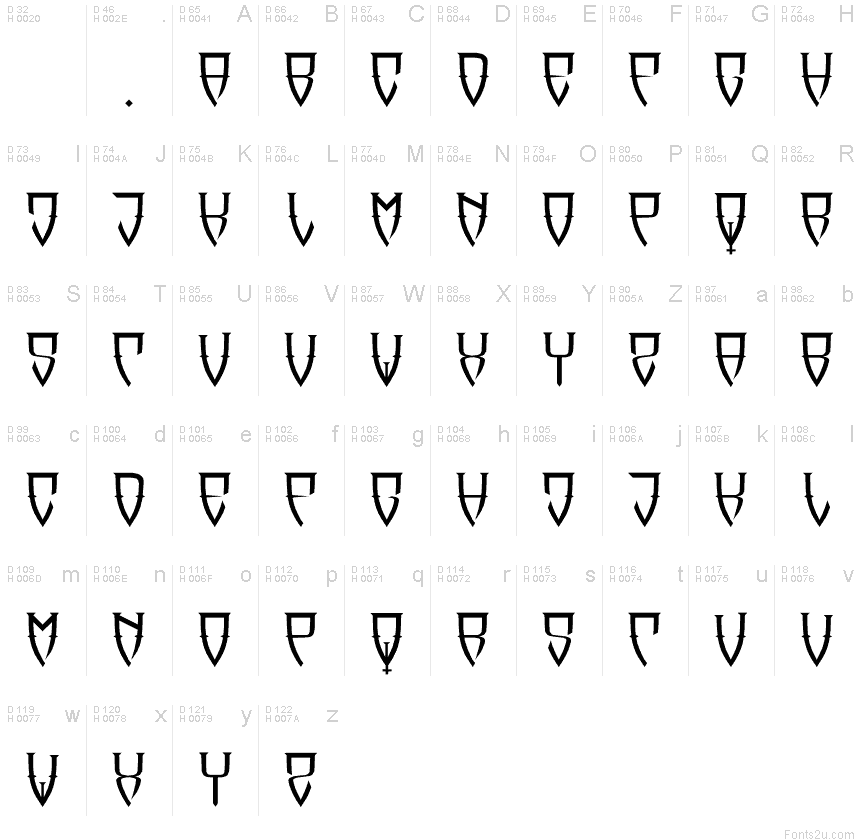
Reubalach di Rzy/SD è un font gotico moderno gratuito composto solo da maiuscole, caratterizzato da un ritmo duro e tagliente. Le lettere sono ridotte all'essenziale del blackletter, con forme superiori ampie che si assottigliano in punte affilate e piccole incisioni a cuneo, mantenendo l'alfabeto austero piuttosto che ornamentale.
È perfetto per poster, copertine di album, titoli di giochi, flyer di eventi e marchi dal mood dark, dove serve un font gratuito con un'atmosfera medievale ma senza fronzoli d'altri tempi. Poiché le maiuscole ripropongono costantemente queste terminazioni a punta e giunzioni nette, Reubalach funziona benissimo anche per titoli brevi, monogrammi e bozze di loghi che richiedono una silhouette forte ed araldica.